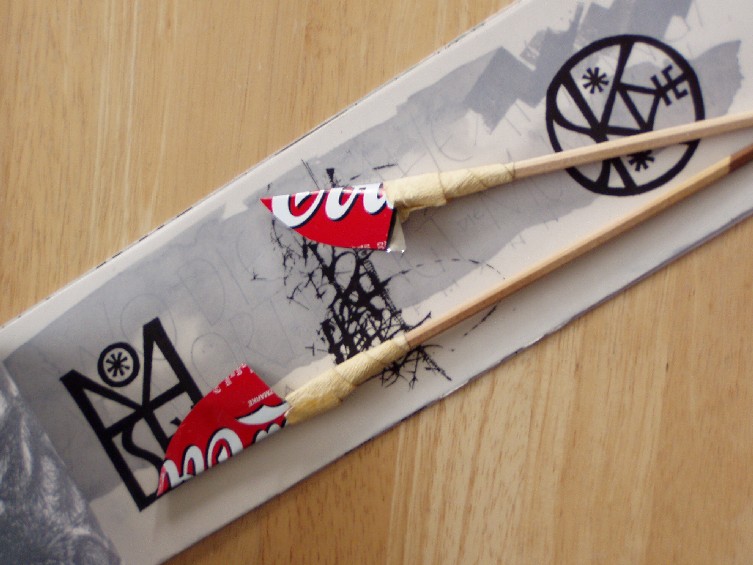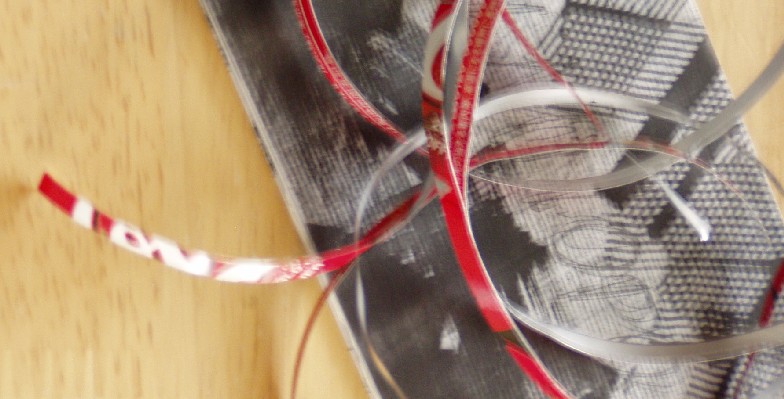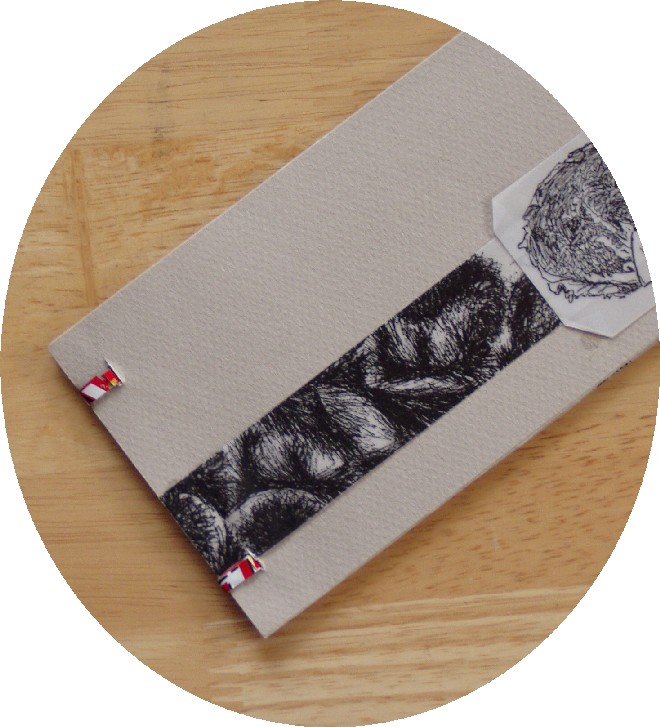
コカコーラを使おうよ!
ワールド・カップの公式スポンサー故か…「コカコーラを飲もうよ〜!」とCMで流れていますが、カリ人にとっては「コカコーラを使おうよ〜!」の方が近いかも…。
コカコーラの缶はアルミです。アルミは柔らかいので、はさみでもチョキチョキ切れます。一番身近な変身はコーラペンと呼ばれるツールです。いろんなカリ人が使いこなしていますが、私が初めてそのペンを見たのはドイツのカリ人インゲボルグによるものでした。彼女が東京に来た際に、わざわざ手製のコーラペンをくれたのでした。
コーラペンは素材の柔らかさから、フレキシブルな動きをします。従って、下地が硬くてもルーリングペンのように滑らないでしょう…。ちょっとクイルに似ているかもしれませんね。以前、ブロディのWSで作った下地にルーリングペンで書いたら下地を彫ってしまいました。そういう状況をcatchしてしまうとブロディは説明してくれましたが…、コーラペンの方がしっかりと書けていたようです。
そのブロディですが、彼のアイデアで、コーラ缶を紐状にカットして本を綴じているのを見ました。「わ〜、ステキ!」ということで、アイデアをいただきました。コーラの缶は赤い色面積が多いので、ワンポイントに使っても目立つし、さし色の効果を発揮します。何かおしゃれ〜。
こんな感じに紐状にカットです。
柔らかくて薄いから、使いやすいですが、あまり折ると「ペキッ」と切れてしまいますから、そこは注意が必要かもしれません。
いい気になって「ゴクゴク」飲むと、お腹も「ボコボコ」…まずいことになるので、お友達とかが飲んだ缶を頂いて、使うのがよいでしょう〜。